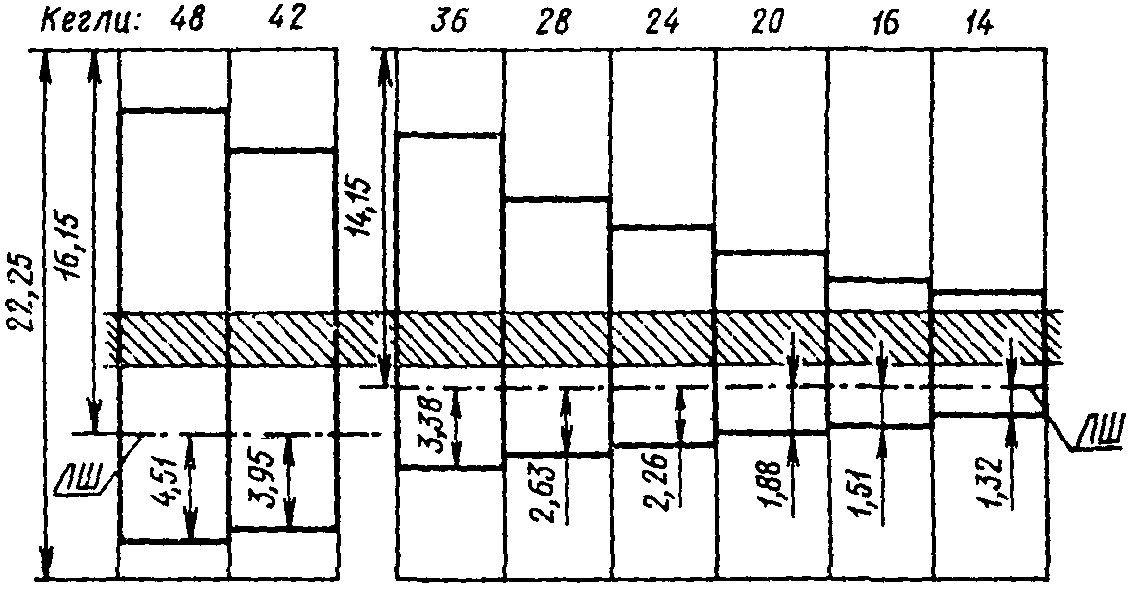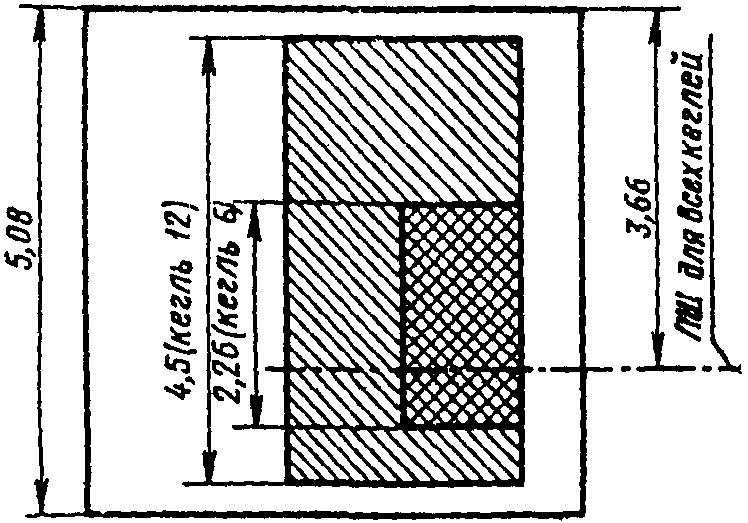
"ГОСТ 3489.1-71. Государственный стандарт Союза ССР. Шрифты типографские (на русской и латинской графических основах). Группировка. Индексация. Линия шрифта. Емкость"
ГОСУДАРСТВЕННЫЙ СТАНДАРТ СОЮЗА ССР
ШРИФТЫ ТИПОГРАФСКИЕ
(НА РУССКОЙ И ЛАТИНСКОЙ ГРАФИЧЕСКИХ ОСНОВАХ)
ГРУППИРОВКА. ИНДЕКСАЦИЯ. ЛИНИЯ ШРИФТА. ЕМКОСТЬ
Printing types (Russian and Roman graphic bases). Group
arrangement. Indexing. Base line. Characters per 4 picas
ГОСТ 3489.1-71
Знак | Частотная характеристика, % |
а | 7,4 |
б | 1,5 |
в | 4,4 |
г | 1,4 |
д | 2,7 |
е (ё) | 7,9 |
ж | 0,9 |
з | 1,6 |
и (й) | 8,2 |
к | 3,2 |
л | 3,9 |
м | 2,7 |
н | 6,0 |
о | 10,4 |
п | 2,5 |
р | 4,6 |
с | 5,0 |
т | 6,0 |
у | 2,3 |
ф | 0,2 |
х | 1,1 |
ц | 0,5 |
ч | 1,3 |
ш | 0,7 |
щ | 0,4 |
ъ | 0,1 |
ы | 1,9 |
ь | 1,5 |
э | 0,2 |
ю | 0,6 |
я | 2,0 |
Н (прописн.) | 2,1 |
. (точка) | 4,3 |
0 (ноль) | 0,5 |